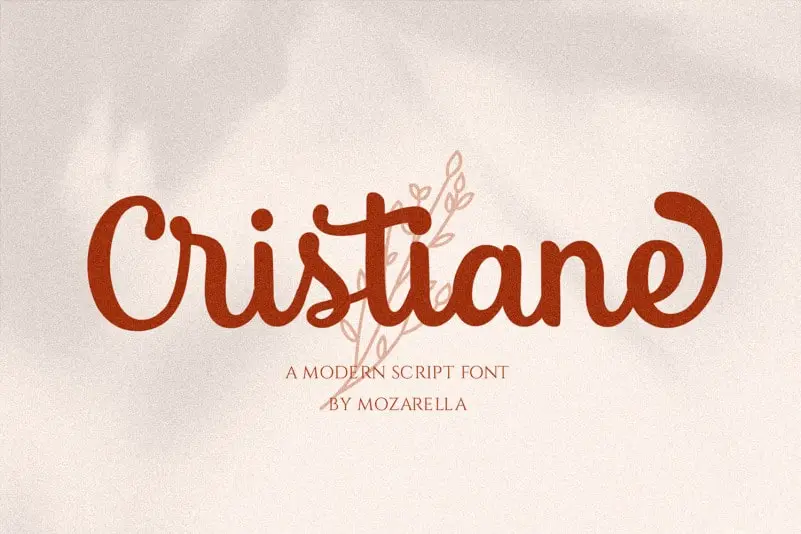
A Cristiane Script Font traz a essência do tipo tipográfico clássico para qualquer projeto design com seu próprio estilo único. Inspirada nos antigos padrões de tipo, essa fonte adquire uma personalidade única que combina um ar descontraído e confortável com sua legibilidade perfeita. Suas letras leves e elegantes são perfeitamente adaptáveis a diversas necessidades, tornando-a versátil sem perder seu charme natural. Como resultado da mão do designer Mozarella, Cristiane Script é uma fonte elegante ideal para aplicativos variados que vão desde editoriais até design gráfico. Um toque de seriedade e um toque de descontração são características desta fonte criada pelo arquiteto de tipos para qualquer projeto em que você desejar dar uma mãozinha com estilo.